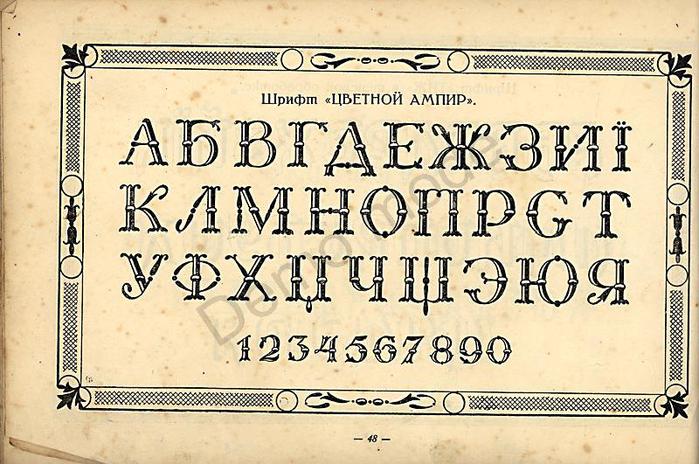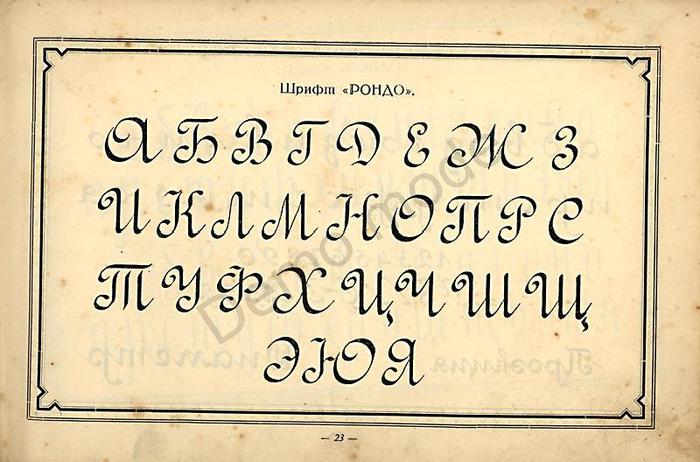
Что такое шрифт? И как используются шрифты? Как вы можете создавать качественные типографские дизайны, используя шрифты наилучшим образом?
Что такое шрифт? Это глиф?
Прежде чем понять, как использовать шрифты, полезно знать, что такое шрифт. И какая разница со шрифтом, глифом и т.д.
Потому что да, шрифт и шрифт не означают одно и то же.
Шрифты в графике, типографике и издательском деле подобны кирпичам в архитектуре, атомам в физике или числам в математике.
Одним словом, они являются основой графического материала.
Набор символов, изученный последовательно и по одним и тем же формальным принципам, образует гарнитуру, файл которой называется шрифтом.
Но давайте лучше проясним эти аспекты.
Шрифты, гарнитуры и глифы
Символ представляет собой букву, знак препинания или символ.
Так, например, буква «А» — это символ.
Этот символ, в свою очередь, может состоять из нескольких глифов, таких как A, a, a или
Набор всех символов и глифов латинского алфавита, оформленных в соответствии с одной и той же визуальной согласованностью и значением, снова берет название шрифта.
И здесь возникают недоразумения в итальянском языке.
Английский более понятен: символ (задуманный как буква) — это character, глиф — это глиф, а связный набор всего этого, шрифт, — это typeface .
С другой стороны, шрифт — это файл
Шрифт — это другое дело: шрифт — это средство, с помощью которого можно применить символ.
То есть: в то время как Garamond — это гарнитура, файл garamond_semibold.otf
Чтобы объяснить это, мы можем провести сравнение с музыкой: если шрифт (персонаж) — это песня, то шрифт — это файл .
mp3, который позволяет нам его слушать. Поэтому неправильно говорить «Послушайте этот mp3-припев!», а гораздо правильнее сказать «Послушайте этот припев песни!».
Поэтому частое использование слова «шрифт» вместо символа является детской ошибкой цифровой эпохи: путать программное обеспечение (средство) с его назначением (конец). Это все равно, что сказать «но это фотошоп», глядя на фотомонтаж.
И это ошибка, которую я сам совершал годами и в которую до сих пор время от времени впадаю. Так что учитесь на моих ошибках!
Почему мы говорим «шрифт»?
Многие думают, что шрифт — это термин английского происхождения, но на самом деле его происхождение — французское. На самом деле это английская транспозиция термина «источник»
из средневекового французского.
Это слово, произносимое как «шрифт» (во французском языке окончание «е» усекается и не произносится), первоначально означало «сплавленный». Латинский корень слова такой же, как у итальянского глагола «таять».
Печатная машина с подвижным шрифтом, изобретенная Гутенбергом в 1455 году.
Имеется в виду именно машина с подвижным шрифтом Гутенберга , которая фактически получала буквы в результате плавления металла.
Затем слово «шрифт» было импортировано в Англию, откуда оно распространилось во все англоязычные страны, а оттуда — во весь мир за последнее столетие.
Вопрос: вы говорите шрифт IL или шрифт LA?
Вечная обличительная речь в мире итальянской графики. Ла Круска сказал, что его можно использовать обоими способами.
Шрифт — слово мужского рода. И это прежде всего потому, что, будучи английским иностранным словом, как и все иностранные слова англосаксонского происхождения, используемые в итальянском языке, такие как
Но что еще более важно, путаница в отношении мужского и женского рода часто возникает из -за большого непонимания происхождения самого слова.
Термин «источник» в средневековом французском языке не имеет того же значения, что и итальянский термин «источник» (например: исток реки)!
Как сказано выше, источник означает слитый! Так и в этом случае использование женского рода бессмысленно.
Итак, резюмируя: ШРИФТ, ОДИН шрифт, ИЗ шрифтов и т. д. Правильно?
Закрывая эту главу, давайте подробно разберем, как делается шрифт и из каких элементов он состоит.
Какие существуют варианты шрифтов и типы шрифтов?
Давайте посмотрим, какие термины идентифицируют, с одной стороны, различные файлы, составляющие семейство шрифтов, а с другой — основные типы шрифтов.
Варианты шрифта (жирность, курсив и т.д.)
Как уже упоминалось, шрифт — это файл, и каждый файл соответствует гарнитуре, в которую вставлены все глифы, предназначенные для совместной работы как единое целое.
Как правило, файлы шрифтов группируются в семейства шрифтов, в которых есть варианты исходного шрифта.
Основные варианты
таковы:
- «Обычные » версии, обычно называемые Roman или Regular.
- Все варианты веса (то есть толщины шрифта), которые могут варьироваться от самых тонких (Light, Thin, Extra-Light и т. д .) до самых толстых ( Bold, Black, Extra-Bold, Ultra и т. д .)
- Курсив, или курсив, который является просто другим шрифтом, разработанным с различными оптическими и эстетическими вариантами (это не просто наклонный обычный шрифт). Курсивные шрифты также имеют свои варианты жирности ( Bold Italic, Light Italic и т. д .).
Текст вашего проекта необходим для его общего успеха. Поиск идеального шрифта привлечет внимание, четко передаст ваше сообщение и хорошо представит ваш бренд.
Эти символы могут быть числами, символами, алфавитами (как строчными, так и прописными) и даже знаками препинания.